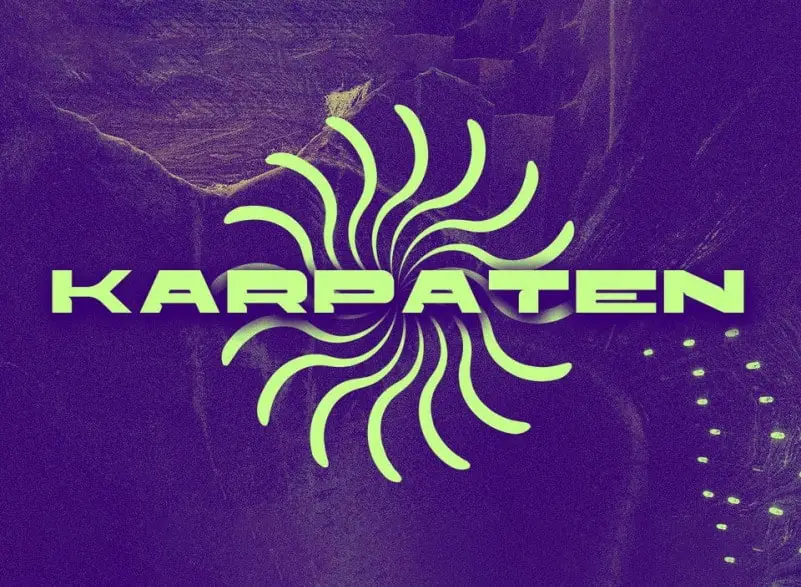
Karpaten Display Font – Download Grátis
Introduzimos a Karpaten Display Font, uma fonte bold e espessada que transmite força e bravura. Ideal para headlines, postais, títulos de marca, camisetas personalizadas e outras aplicações gráficas. Foi criada por Luis H. J. Rapp, um designer de fontes do 99designs. Uma fonte tipo display totalmente gratuita, combinando uma aparência larga e agressiva com detalhes refinados menores. Todas as letras possuem o mesmo espaçamento (exceto a letra I). Experimente a Karpaten Display Font para dar um toque único em seus projetos gráficos.